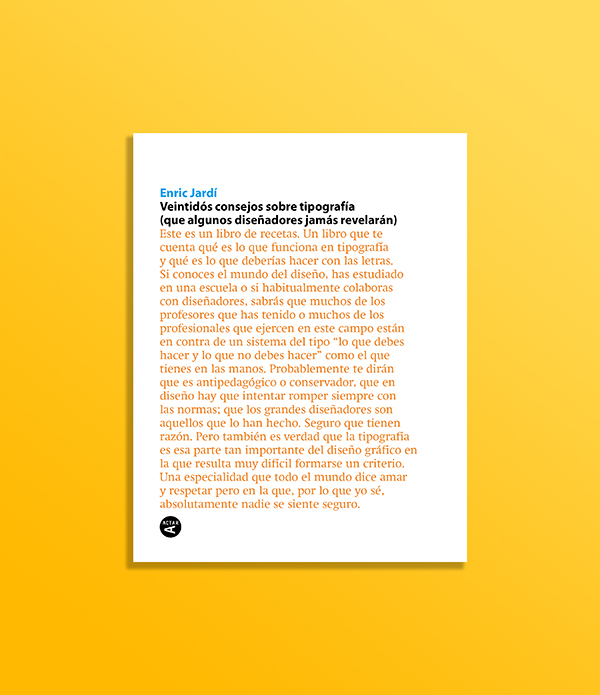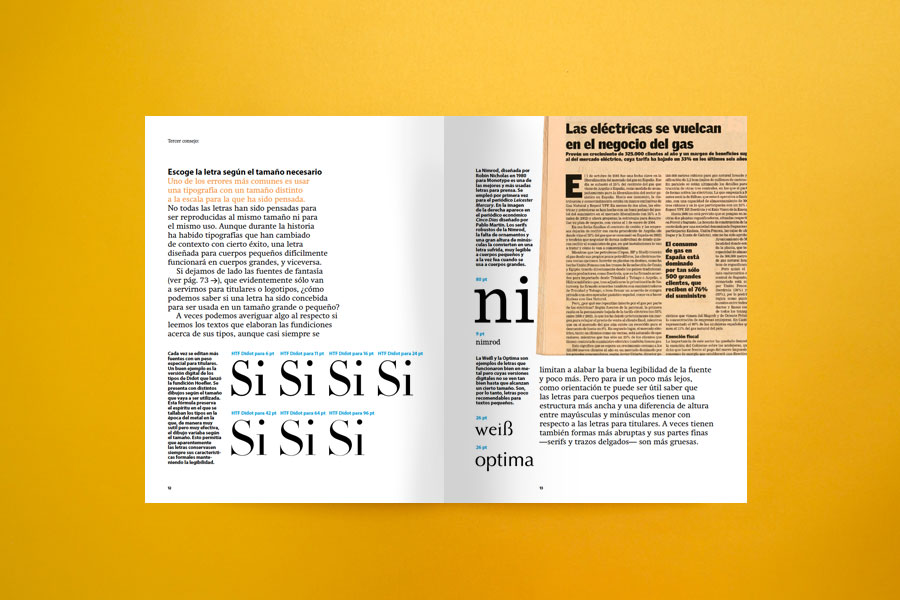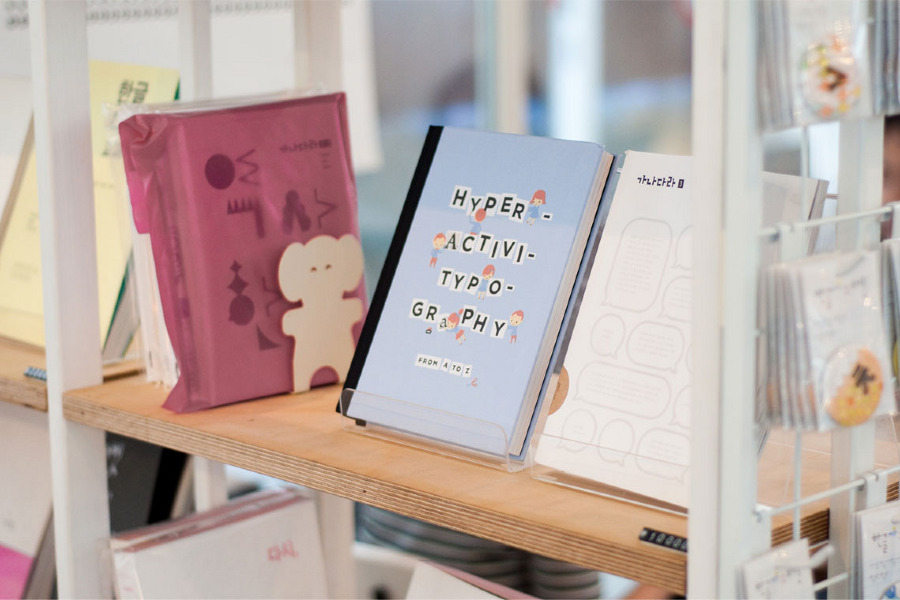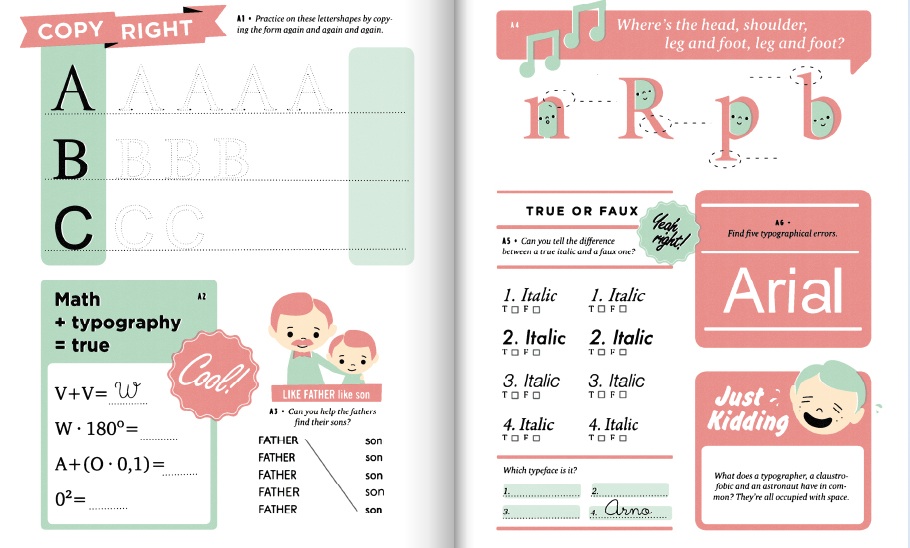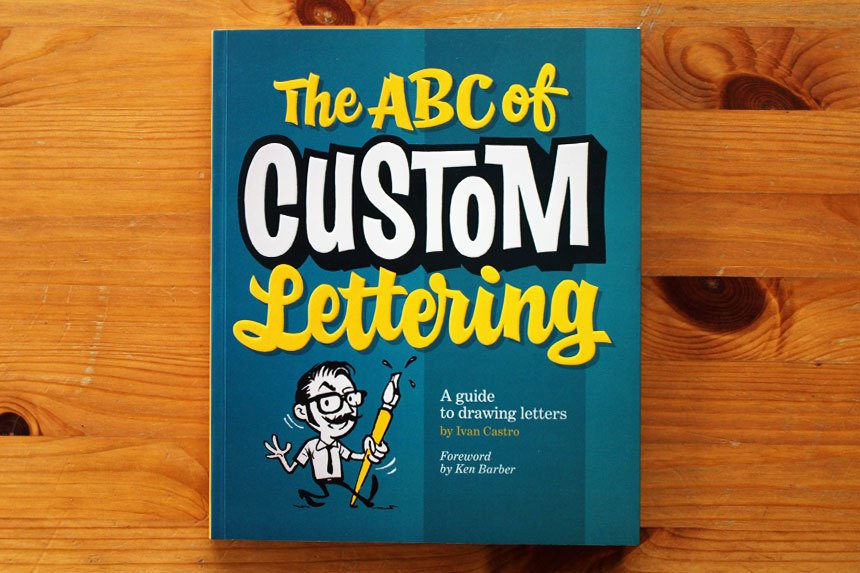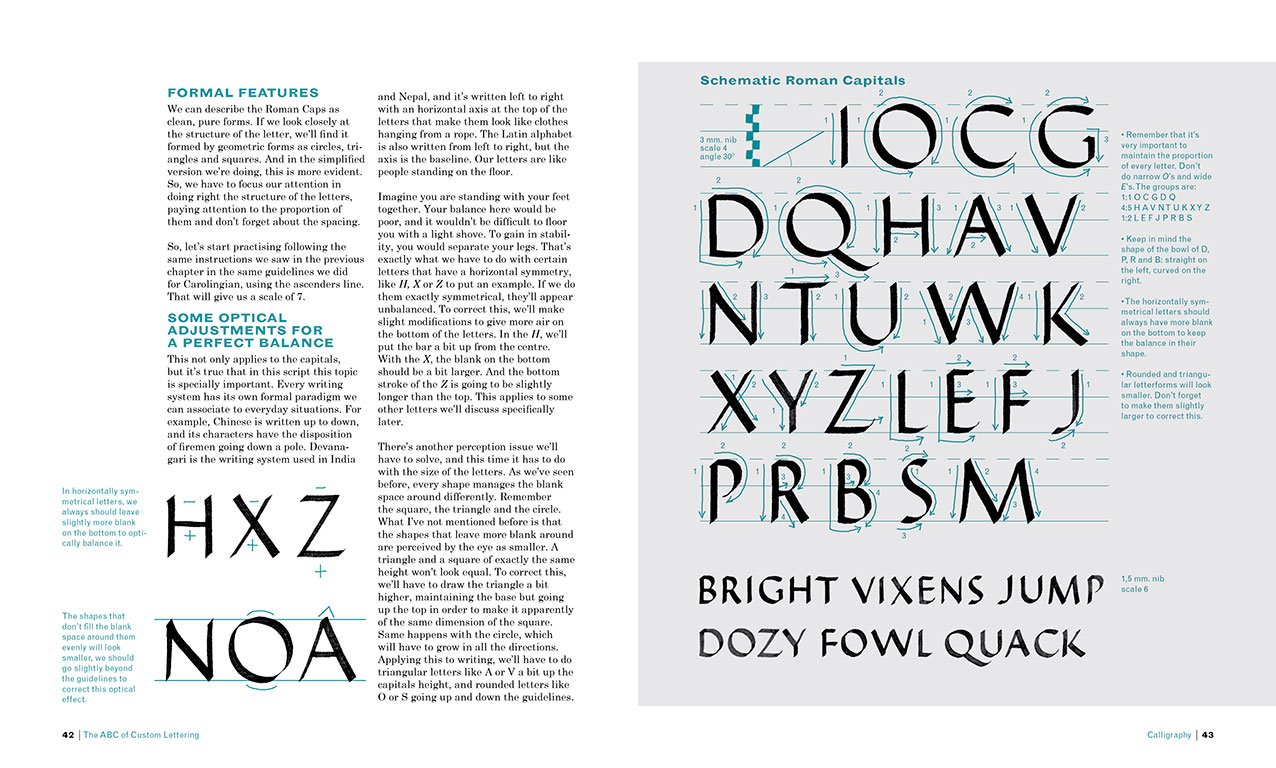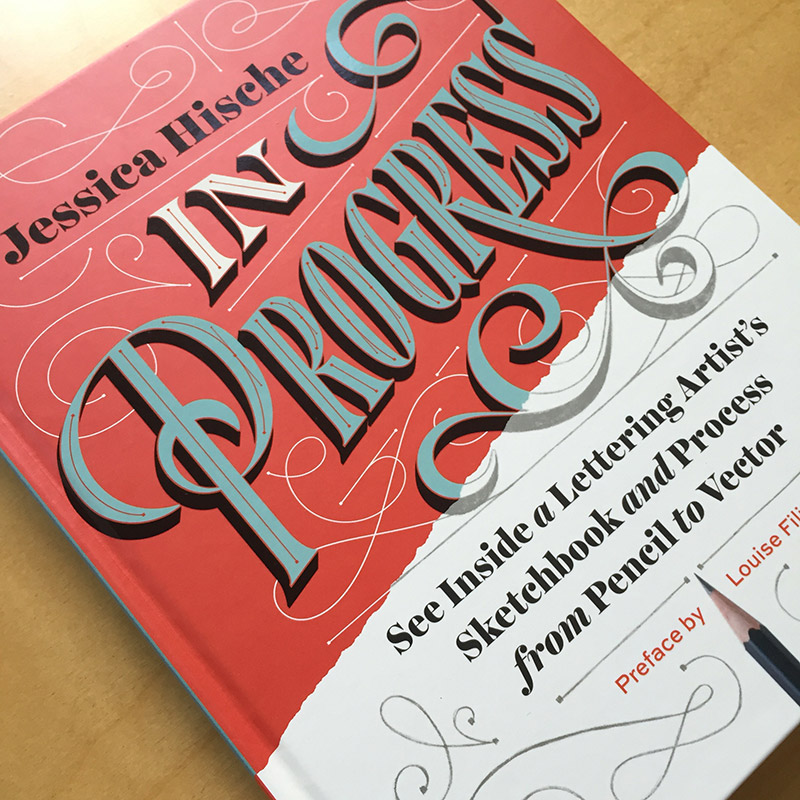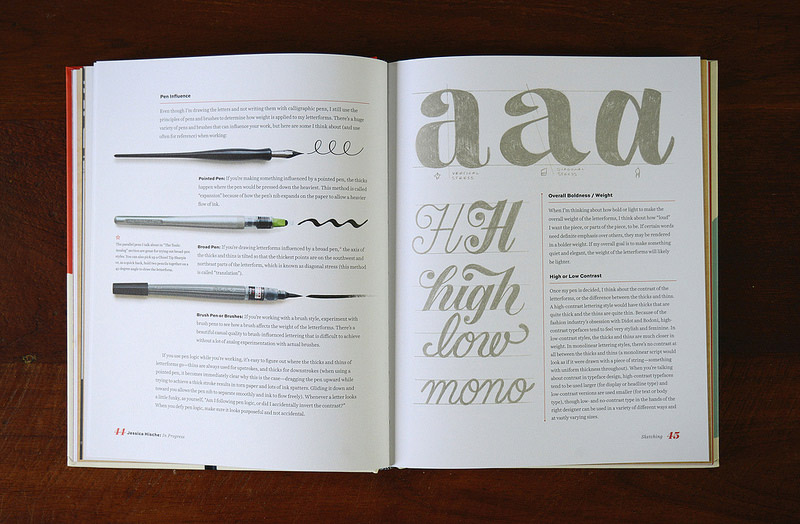
5 Libros de tipografía y lettering imprescindibles
Recopilación de nuestros libros de tipografía y lettering más preciados
¿A que sabéis qué día es hoy? Exacto, es el Día del Libro, todo el mundo lo sabe. Las newsletters de esas tiendas online en las que alguna vez compraste un libro te lo llevan recordando toda la semana, los blogs que sigues también; la gente en Twitter parece leer más esta semana que nunca.  Para no ser menos, nosotros hoy os traemos una lista de 5 libros de tipografía y caligrafía que son imprescindibles para vuestra biblioteca. Porque sabemos que el Día del Libro siempre cae alguno, ¿y qué mejor que comprar un libro para aprender cosas bonitas?
1. Thinking With Type – Ellen Lupton
Este libro de tipografía es el más imprescindible de todos los que vamos a recomendar hoy. En él, Ellen Lupton (diseñadora gráfica, tipógrafa y escritora), hace un repaso a la tipografía que se divide en 3 secciones. En la primera, nos habla de la letra, orígenes, formas y todas las características que la hacen ser como es (anatomía, tamaño, clasificación, familia, ornamentos, lettering, etc.). En la segunda, se centra en el texto, y es donde entran conceptos como el kerning, el tracking, la alineación, la jerarquía o la composición de párrafos. En el último bloque, nos hace una introducción al concepto de grid o maqueta, los tipos de grid que existen, cuándo conviene usarlos, etc.
Es un libro teórico en el que abundan los ejemplos y en el que los aspectos teóricos se complementan con una serie de ejercicios prácticos muy útiles para afianzar conceptos. Como comentamos, es imprescindible tanto para diseñadores gráficos y tipógrafos como para estudiantes de cualquiera de estas disciplinas.
2. Hyperactivitypography from A to Z – Studio3
Una de las formas más bonitas y geniales de aprender es jugando y eso es lo que nos ofrece este libro de título trabaléngüico, desarrollado por los mismos autores que A History of Graphic Design For Rainy Days, Hyperactivitypography nos invita a sumergirnos de lleno en el mundo de las letras a través de un juego ilustrado y colorido que comienza en la A y termina en la Z. Por el estilo naíf de las ilustraciones y la paleta de color que predomina en el libro, podrías pensar así de primeras que se trata de un libro infantil, para enseñarles a los más pequeños de la casa de qué va todo este invento de la tipografía, pero en cuanto le echas un vistazo te das cuenta de que ese pensamiento no podía estar más alejado de la realidad.
Dentro del mundo de los libros de tipografía, es un libro complejo y que requiere un profundo conocimiento tipográfico y de diseño para poder ser completado. Por ejemplo, uno de los juegos es adivinar en un reloj con números de tipografías sans serif a qué tipografía pertenece cada número, en otro hay que distinguir qué itálica o negrita es real y cuál está hecha dándole al botón de negrita o itálica de un editor de texto, etc. Pero gracias a él puedes aprender muchísimas cosas curiosas sobre tipografía y también sirve para entrenar el «ojo tipográfico», esa habilidad de saber identificar casi cualquier tipografía solo con verla.
3. Veintidós Consejos sobre tipografía – Enric Jardí
El mundo del diseño gráfico es como la vida misma, nada se aprende mejor que tras haberte equivocado cientos de veces, y de esto, creemos que nace este famoso libro de Enric Jardí en el que nos da veintidós consejos para hacer un buen uso de la tipografía y además otros veintidós consejos sobre qué errores no cometer con ella. Alguno pensará «bueno ya hay libros de tipografía que te dan consejos sobre qué hacer y qué no»; entonces, ¿qué diferencia a este de otros libros de tipografía? Lo primero es su estilo; un estilo directo, sin rodeos, consejos de una línea que explica en una o dos páginas, dependiendo su complejidad.
Además, no se pierde en aspectos teóricos que pueden aburrir al lector; es un libro eminentemente práctico y basado en la experiencia, que hará que cualquier persona que se esté iniciando en el mundo del diseño gráfico o que esté empezando a componer texto no cometa errores salvajes, como trabajar en español con una tipografía que no tenga tildes o virgulilla, combinar tipografías muy parecidas, etc. Asimismo, da consejos de composición y estilísticos más avanzados, para ayudar al lector a que sus composiciones tipográficas sean lo más perfectas posible.
4. The ABC of Custom Lettering – Iván Castro
Otra gran forma de aprender tipografía es recurrir a los libros de lettering. ¿Por qué? Pues porque al tratarse de libros de tipografía que te enseñan a dibujar letras y darles un estilo propio, tienen un gran contenido teórico de construcción tipográfica que otros libros sobre la materia pueden no contener, al centrarse más en aspectos de identificación y composición que en la creación de tipos. Este libro de Iván Castro es especialmente interesante porque parte desde los aspectos más básicos del lettering, es decir, qué papel, qué instrumentos usar, cómo dibujar los distintos estilos de letras, etc., hasta llegar a explicar con trabajos del autor el desarrollo completo de un trabajo de lettering.
Pero como decíamos anteriormente, lo mejor de este libro es la cantidad de información sobre construcción tipográfica que contiene, Iván debe ser uno de los mayores amantes de la caligrafía de este planeta y eso se nota en el mimo con el que toda la parte de desarrollo tipográfico está hecha; empezando por una introducción a las bases de la caligrafía seguido por secciones en las que, a modo de guía, explica cómo dibujar los estilos de letra más importantes, empezando por la Romana Moderna y la Sans Serif, y llegando a otros más complejos como la Latin, la Script o la Interlocked
5. In Progress – Jessica Hische
in progress jessica hische libros de tipografía y lettering
A estas alturas del juego de la vida todo el mundo sabe quién es Jessica Hische, la diseñadora y tipógrafa más adorable del panorama del diseño gráfico mundial. Su libro recoge sus trabajos más destacados a modo de case study, es decir, que se ve el desarrollo completo, desde el briefing y los bocetos a las distintas piezas finales. Además de esto, muestra todas las herramientas con las que trabaja y enseña su proceso de digitalización. Una de las mejores cosas que tiene es que muestra muy bien el vectorizado de las tipografías haciendo mucho hincapié en la forma correcta de colocar los manejadores de los puntos de ancla para que las curvas sean suaves y armónicas, además de dar muchos consejos compositivos.
in progress jessica hische 2 libros de tipografía y lettering
No nos extenderemos mucho porque ya hablaron de este libro nuestros compañeros de Sleepydays, de hecho, han hablado de Jessica en varias ocasiones. Se trata de un libro mucho menos teórico que el de Iván Castro, pero muestra un proceso diferente y muy divertido de enfrentarte a un proyecto de lettering.